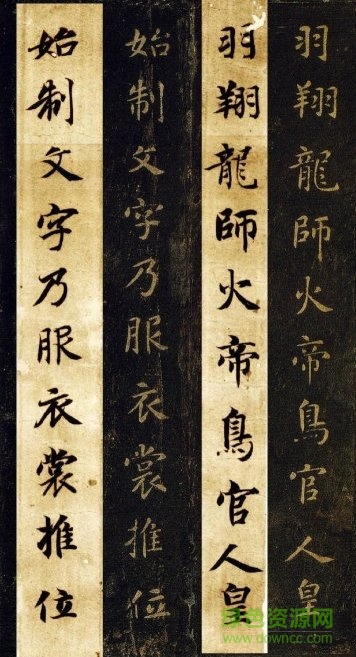
智永是王羲之后人,書傳家法,對(duì)后世書法影響甚遠(yuǎn)。董其昌評(píng)價(jià)其字“力透紙背”,蘇軾評(píng)其字“精能之至,返造疏淡”,何紹基評(píng)曰“含蓄而極富韻律意趣”。智永楷書,易上手易轉(zhuǎn)體,自然舒展,而其楷書《千字文》堪稱典范,是一千多年來最佳版本。
文字全面、信手拈來
在《智永千字文》里,一千字字字不重,常用字在里面基本都能找得到,這就意味著,哪天你想寫《靜夜思》會(huì)突然發(fā)現(xiàn)竟能信手拈來,這種感覺太爽了!若學(xué)個(gè)字偏字少的帖,就等著哭暈在廁所吧。
具備很強(qiáng)的“支點(diǎn)”意義
智永楷書筆法豐富,便于進(jìn)入其他書體的學(xué)習(xí)。智永的楷書自帶行意,也就是說你寫楷書時(shí)已經(jīng)預(yù)習(xí)了行書;欲學(xué)小楷?智永這種露鋒狀態(tài)與小楷暗合,給小楷打底,頗為合適;想學(xué)個(gè)篆隸?相比其他楷書,智永至少不給你擋路?。?/p>
書寫性強(qiáng)、實(shí)用性強(qiáng)
“書寫性”是個(gè)啥?說白了就是日常的、不刻板的書寫狀態(tài)。這是其他很多楷書所不能比的。比如你用智永楷書和柳體楷書分別寫幅對(duì)聯(lián)對(duì)比看,哪個(gè)更加精致且活躍?這就是寫很多唐楷導(dǎo)致筆畫間孤立無聯(lián)的原因,這也是智永楷書的最大優(yōu)勢(shì)之一。
系罕見珍貴墨跡
墨跡字跡、線條、筆觸清晰,當(dāng)為學(xué)書優(yōu)選。而我們常見的唐以前的書法多為經(jīng)過刻工斧鑿的碑刻,加上年久風(fēng)化,已與書寫的真實(shí)狀態(tài)相去較遠(yuǎn)。能見到《千字文》如此珍貴的墨跡本,實(shí)屬不易,非常珍貴,是學(xué)楷之極佳范本。